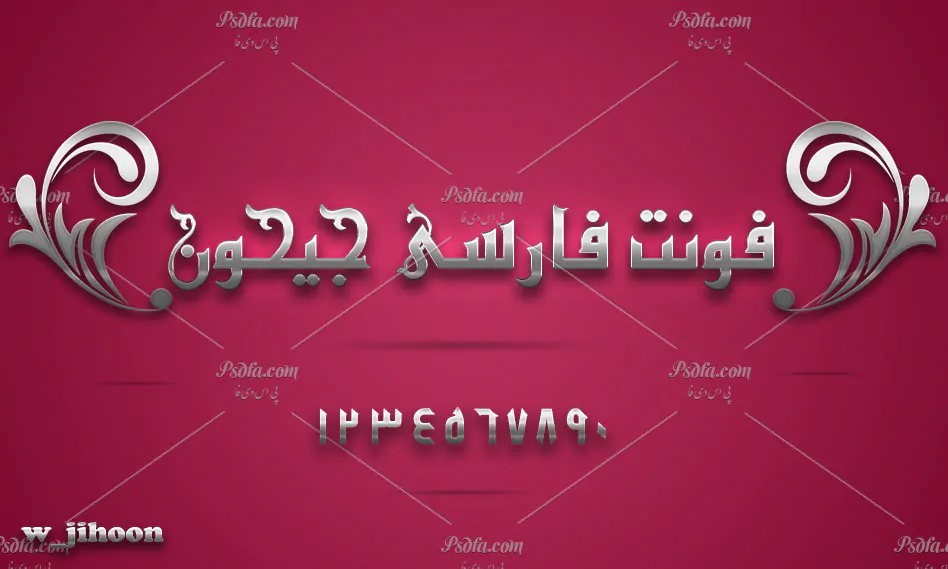
فونت جیحون مناسب جهت استفاده در طراحی و گرافیک
فونت فارسی جیحون
در این مطلب شاهد فونت فارسی جیحون مناسب جهت استفاده در طراحی و گرافیک می باشید. فونت فارسی جیحون یکی دیگر از سری فونت های فوق العاده زیبای فارسی است که با فرمت ttf در سایت قرار داده شده است. پس از دانلود و خارج سازی آن از حالت فشرده توسط نرم افزار Winrar و نصب آن در پوشه فونت های سیستم قادر خواهید بود این فونت زیبا را در تمام نرم افزارهای گرافیکی و ویرایشگر متن همچون نرم فزار فتوشاپ ، مجموعه نرم افزار آفیس و … مورد استفاده قرار دهید. از این فونت زیبا می توان در طراحی انواع پوستر ، بنر ، تراکت و … مخصوصا در طراحی بنر و پوسترهای مذهبی استفاده نمود. اگر از طراحان بنر و پوسترهای مذهبی هستید به شما پیشنهاد می کنیم این فونت زیبا را از دست ندهید و از آن در پروژه های خود استفاده کنید.